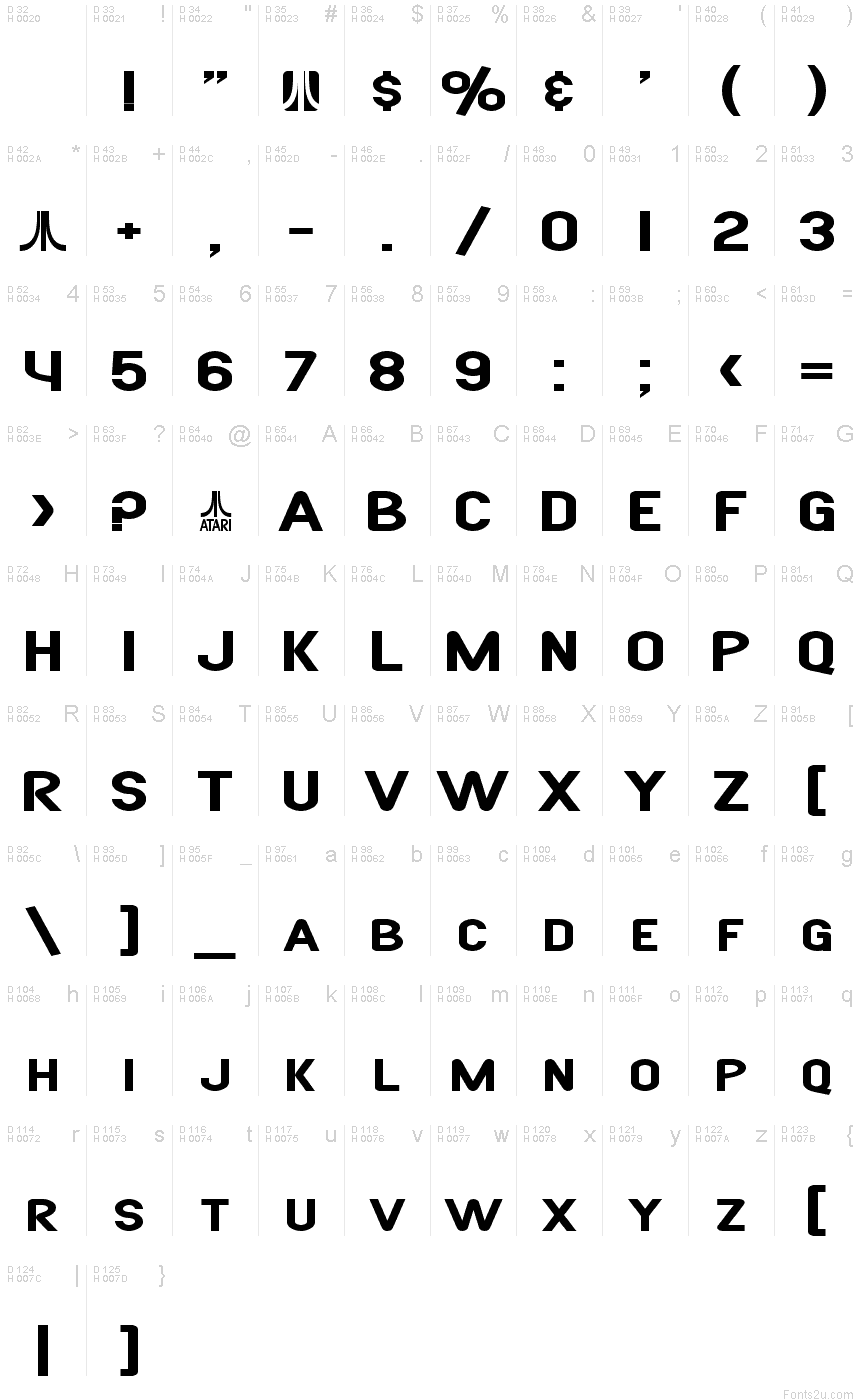
SF Atarian System Extended Bold od ShyFoundry to darmowy krój typu display w stylu retro-futurystycznym, który bazuje na wyrazistej geometrii i klimacie wczesnych gier arcade. Litery są ciężkie, szerokie i mają precyzyjne cięcia. Szerokie, horyzontalne kształty oraz ostre, trójkątne łączenia nadają krojowi szorstki, syntetyczny rytm.
Font świetnie sprawdza się w logotypach gier, plakatach sci-fi, okładkach albumów, planszach tytułowych i opakowaniach technologicznych, gdzie potrzebujesz elektronicznego nastroju lat 70. i 80., unikając przy tym parodii. Dzięki temu, że jest darmowy, doskonale nadaje się też do krótkich nagłówków i monogramów – masywne litery tworzą solidną, blokową sylwetkę nawet przy użyciu zaledwie kilku znaków.
SF Atarian System Extended
ShyFoundry
Derek Vogelpohl